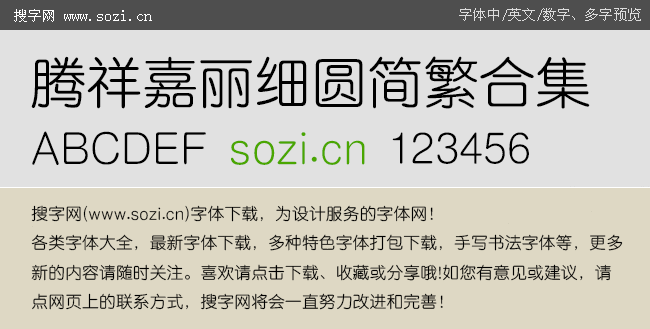
騰祥嘉麗細(xì)圓簡(jiǎn)繁合集
搜字網(wǎng)提供一款騰祥嘉麗細(xì)圓簡(jiǎn)繁合集中文藝術(shù)字體下載,騰祥嘉麗細(xì)圓是一款應(yīng)用于設(shè)計(jì)方面的簡(jiǎn)體中文漢字,該字體線條簡(jiǎn)潔圓潤(rùn),字形大方得體,整體效果出眾,并且字庫(kù)完整,可用于藝術(shù)設(shè)計(jì)、包裝印刷、簽名設(shè)計(jì)、圖形設(shè)計(jì)等領(lǐng)域。